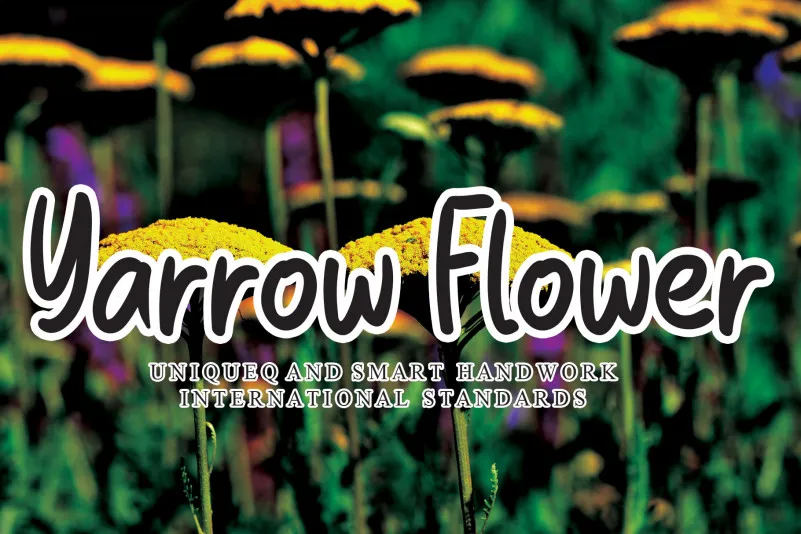
A ‘Yarrow Flower Script Font’ é uma elegante fónta escrita a mão que traz sutileza e delicadeza para projetos personalizados. Ideal tanto para aniversários e convites como para qualquer projeto de decoração artesanal que busque um toque romântico, esta fonte se destaca como uma escolha perfeita para criar mensagens únicas e carregadas de emoção. Seja você que está buscando adicionar um toque especial a cartões de aniversário ou envelopes de correspondência, ou alguém desejando personalizar projetos de decoração em casa, essa fonte escrita a mão é uma ótima escolha para capturar a essência delicada e encantadora do momento. Com sua elegância única, ela oferece ao usuário um meio criativo para transformar frases simples em mensagens memoráveis, fazendo com que cada projeto seja um verdadeiro reflexo da personalidade dele.